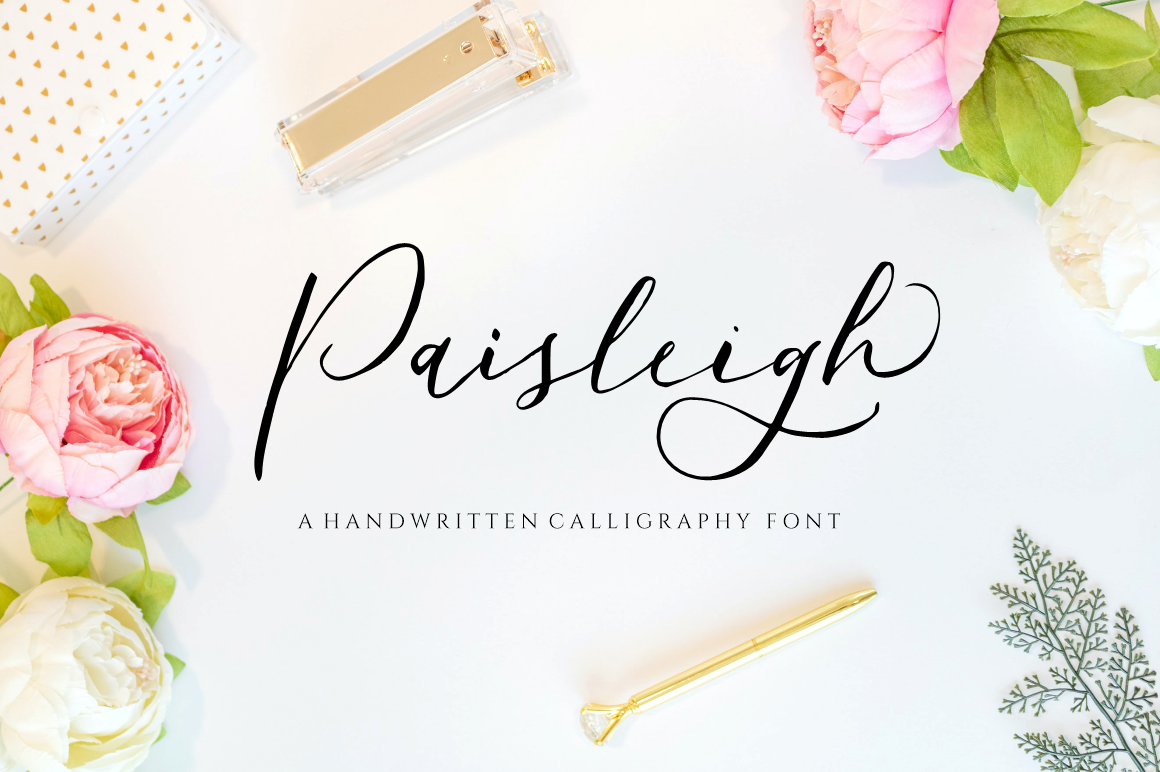
A fonte Paisleigh Font é uma elegante escolha para quem busca trazer um toque artesanal à sua obra, seja ela um livro infantil ou um design de marca. Desenvolvida por ReyreyBlue, essa linhas de escrita cuidadosamente trabalhada e fluidas têm o poder de transformar qualquer ideia de projeto em algo único, destacando-se do resto da coleção com uma beleza que desperta emoções sutis. Seja você um artesão ou designer gráfico, a Paisleigh Font oferece o ideal para aqueles que buscam uma fonte capaz de expressar nuances delicadas e elegância no design. Sua forma fluida cria linhas suaves, fazendo do processo de escrita um momento de criatividade relaxante e lúdico ao mesmo tempo em que garante a qualidade profissional necessária para um trabalho bem-sucedido. Esta fonte é perfeita para quem valoriza cada detalhe, desde os traços finos até as fluididades sutis de uma escrita manuscrita meticulosa.